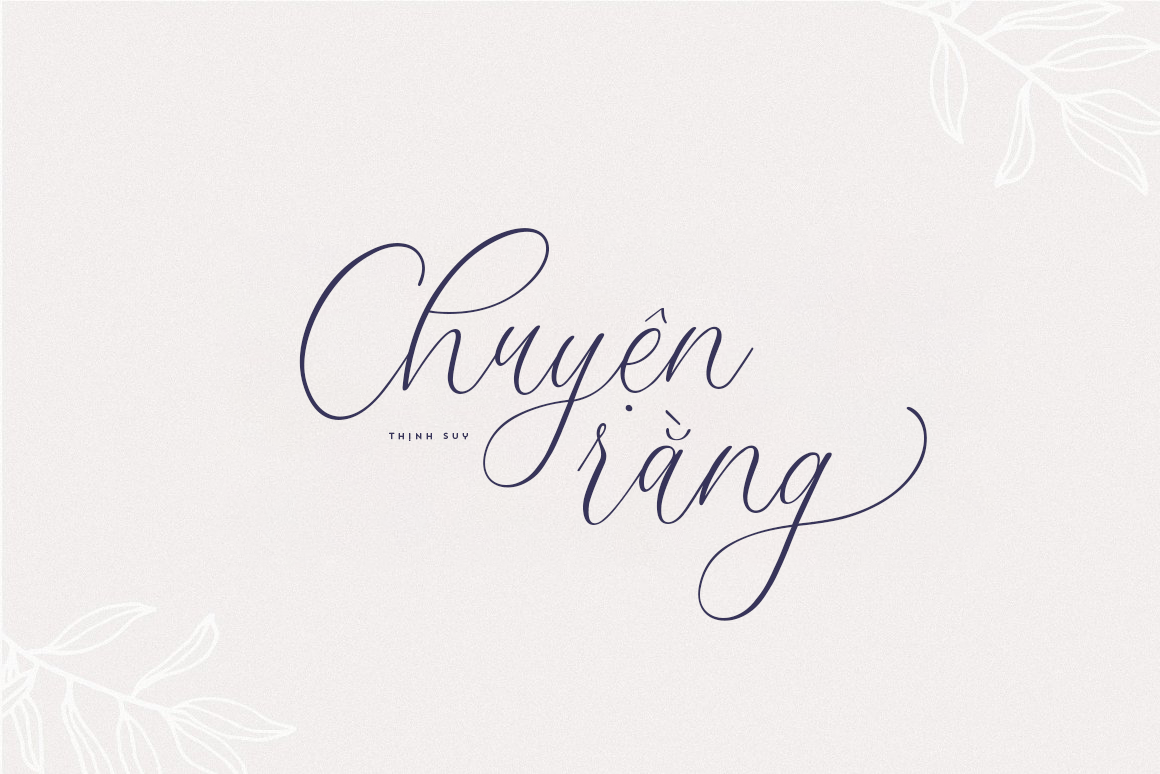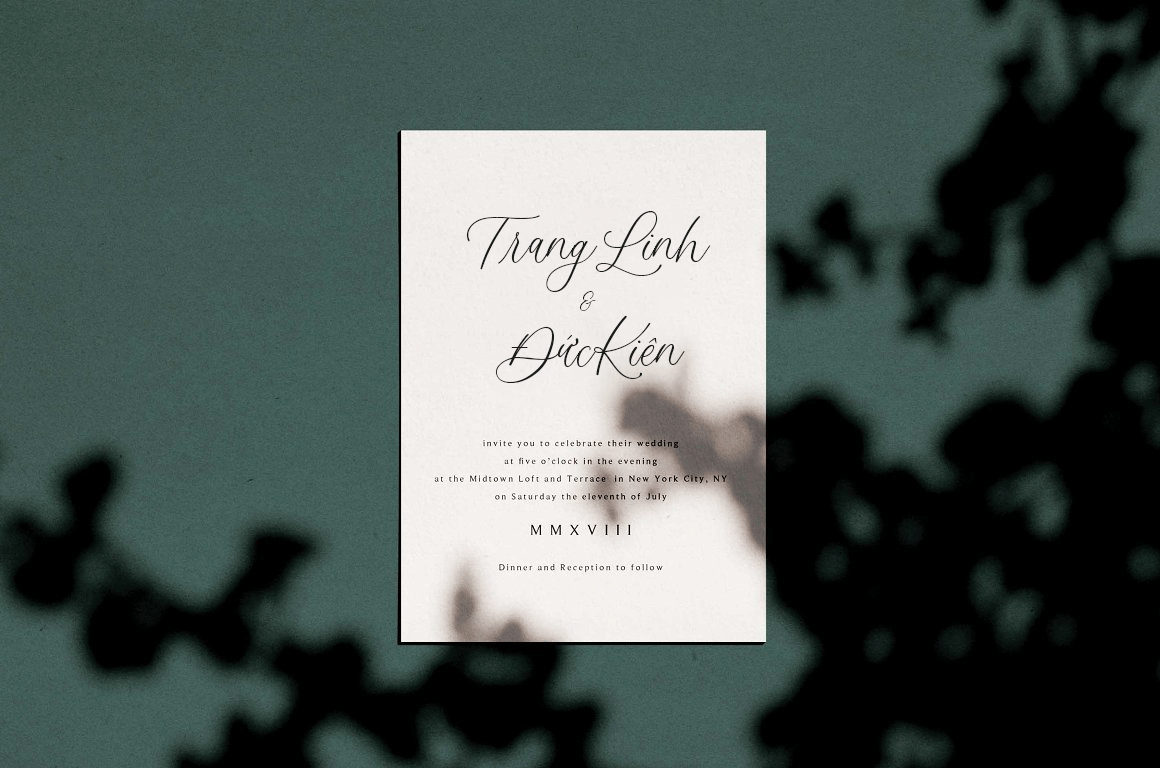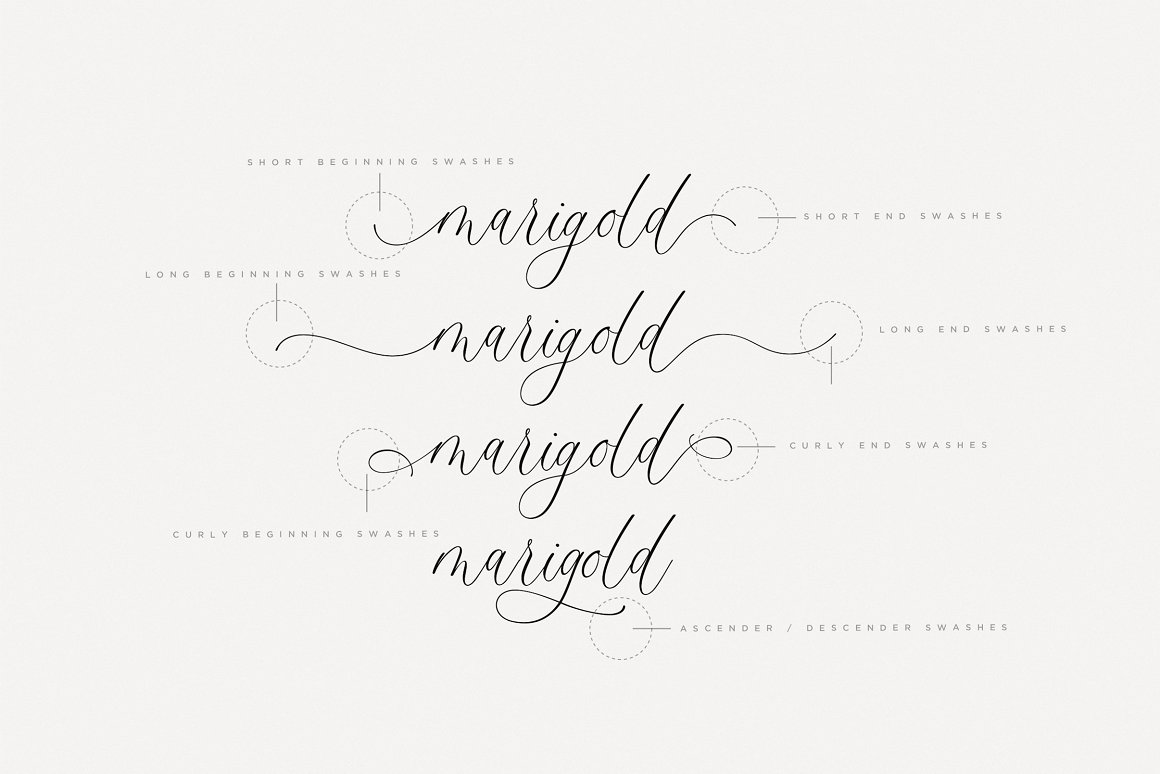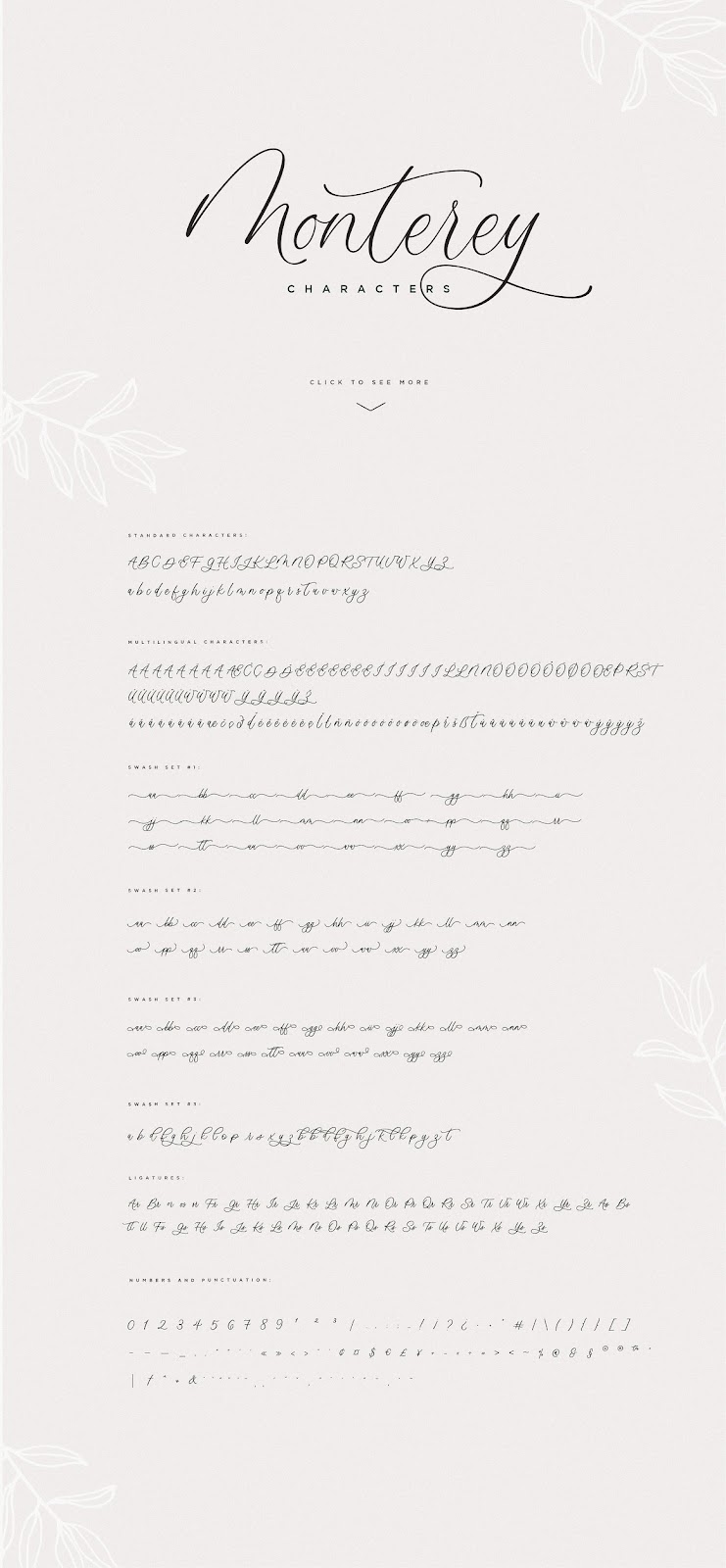
Montery Script – Font chữ viết tay Việt Hóa cực đẹp
Font Montery Script Việt Hóa – được xây dựng với các tính năng OpenTyple và bao các chữ ghép thay thế. Font được việt hóa bởi iCiel, đây là một font chữ viết tay theo trường phái modern calligraphy, phù hợp với nhiều thiết kế khác nhau như thiệp cưới, thiệp mừng, các ấn phẩm trang trí, quảng cáo, các thiết kế youtube, video, photography, typography…
Montery Script được Việt Hóa đầy đủ, kerning, features và tối ưu lại, ngoài ra font còn bao nhiều kí tự alternate cho các bạn thỏa sức sáng tạo, có thể nói đây là một font chữ viết tay việt hóa cực ấn tượng.